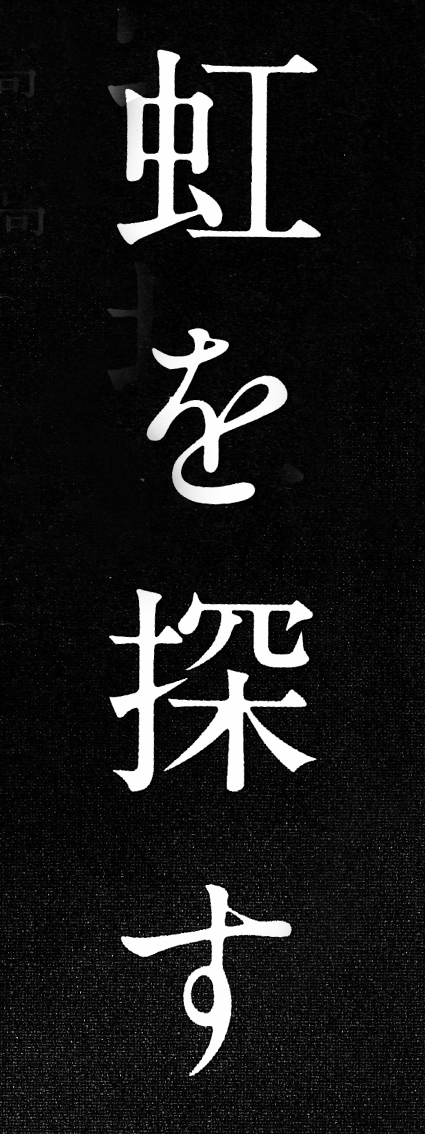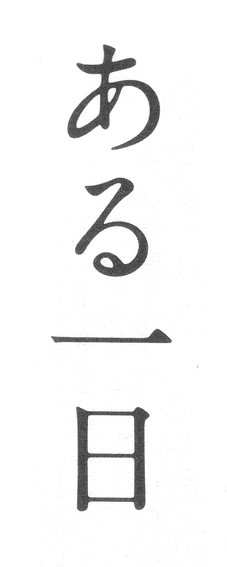
A1明朝
季節の変わり目になると、化粧品の広告にどうしても目がいってしまう。
私は昔から肌が弱いので、実際に使える化粧品は限られていたりするのだが、ファンデーションは新しければ新しいものほどいいとか、新開発の浸透技術だとか書かれると(それでなくても文字に惑わされやすい性質なので)、気もそぞろに新製品を眺める。
すると、時々、化粧品のイメージ写真で、いかにも高級そうな美容液やクリームのびんが、うっすらと汗をかいていることがある。容器の表面できらきらと光を散らす、ふっくらまるい水の粒。
もちろんそれは撮影上の演出だ。誰がみてもわかる。
中身の効果のほどは、写真では確かめようがないけれど、無機質なパッケージを単純に並べて撮っただけのものよりも、何だか良さそうにみえる。水をはじく若葉のような、みずみずしい肌を連想させる。
文字の世界でも似たような演出が行われていることは、でもあまり知られていない。
どんなに心地いい言葉でも、あるいはありふれた言葉でも、選ばれる書体によって、今朝とれたての野菜と、三日前から冷蔵庫に入っていた野菜くらいの違いがある。
その、いわば「朝摘み感」ともいうべきみずみずしさを、私がもっとも感じる書体が〈A1明朝〉である。
〈A1明朝〉はモリサワの伝統的な明朝体のひとつで、かつては〈太明朝体A1〉という名前で愛された写植書体だった。
創業間もない1960年頃、写真植字機の技術では業界をリードするものの、書体の数では写研に水をあけられていたモリサワが「初めて独自開発した太明朝体」であるという。
その優雅でやわらかな表情に、写研の名書体〈石井中明朝体 (MM-OKL)〉の面影があると言うひともいるけれど、私はそうは思わない。〈石井中明朝〉が透明なゼリーだとするなら、〈A1明朝〉はさらに水分量が多くて、溶液に近いような印象がある。
実際の書体見本の解説によれば、「デジタル書体化にあたって、写植特有の墨だまりを再現」したということだが、この「墨だまり」という言葉、辞書をひいても載っていない。書道独特の用語で、ひいては印刷の不安定な滲みや「ボケ味」の意味でもつかわれる場合があるようだ。
この文字でかかれた言葉の、高いところからピチョンと落ちてきたしずくのような感じは、この「墨だまり」と呼ばれる部分から生まれているのだろうか。
世の中が〈石井明朝〉一辺倒だったころ、ふっと何気なく(でも間違いなく確信犯で)つかわれている〈A1明朝〉は、とても印象的だった。違和感とも呼べないほどの差異なのに、そこだけふしぎな浮遊感があった。
そんなイメージのせいか、〈A1明朝〉で読むなら、(私の勝手な好みだけれど)スタッカートのような短い言葉がいちばん好き。
しずくとしずくが、くっつきそうで、絶対にくっついてしまわない程度の、絶妙な距離を保っているときの緊張感が好き。
いつからそんなふうに感じるようになったのだ、と聞かれても答えられないのだが、自分で発見したというより、誰かの記憶を映像みたいにみているような気がする。
それにしても、近頃は本当にこの書体をよくみかける。
霧吹きでぱっぱと水をかけるような気軽さで、たっぷりと潤った言葉が溢れていて、文字の世界もさながら美白ブームのよう。
ところが最近、小説でもたまにみかけるのだが、この書体でびっしり組まれた長い文章を読んでいると、水気の多いサラダを食べているみたいで、ふっと「読む気が失せる」ことがある。本を読みたいのに。好きな作家なのに。
そんなのはあんただけだ、変なやつだなあと言われても仕方ないけれど(笑われるよりむしろ気の毒なやつだと同情されるかもしれない)、でも、やっぱり、錯覚ではないと思う。
「活字中毒」という言葉が昔からあるくらいなんだもの。私と似たようなことを考えているひとが、絶対にいないとも限らないので、思いきって書いてみた。
味に口うるさい常連客を気どっている私のような人間は、まだいい。
「読む気が失せた」理由など、わざわざ考えようとしない一見の読者が大多数である。そのことのほうがこわいと私は思う。